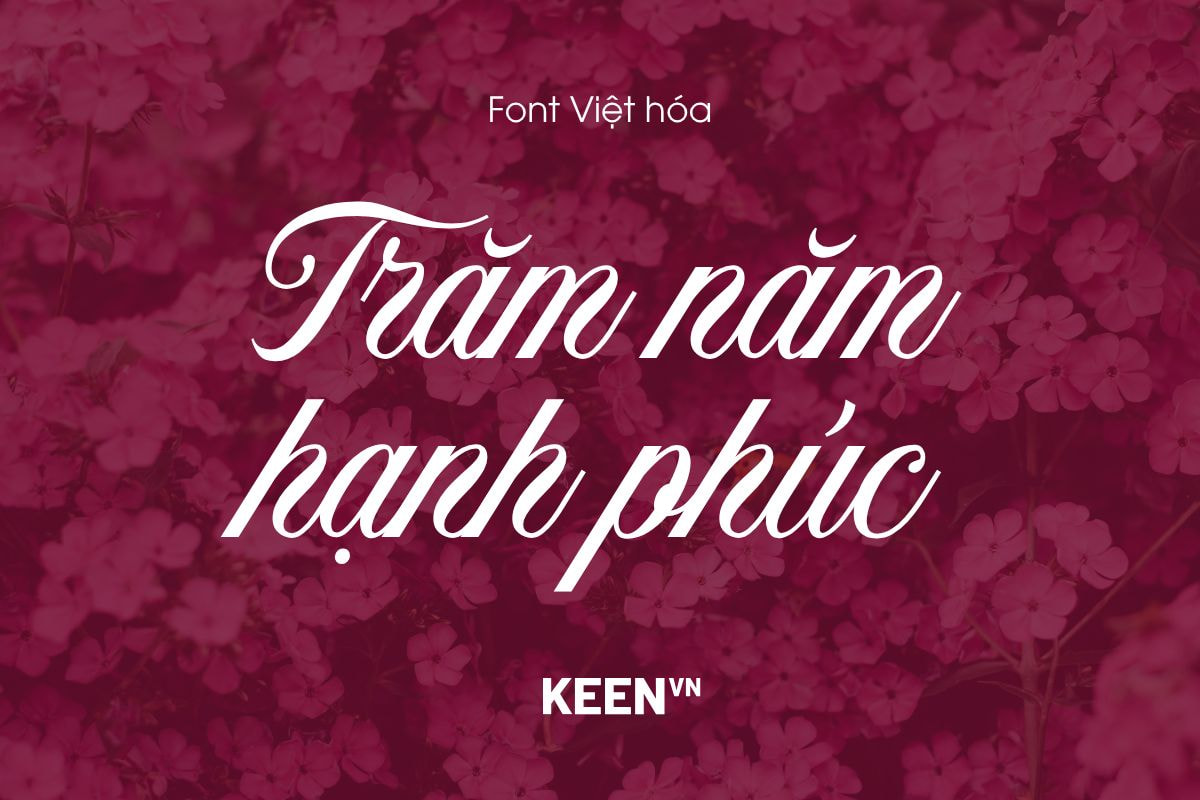
Font Việt hóa NVN Neography
- Hỗ trợ đầy đủ dấu tiếng Việt
Neography là một font script đẹp với các nét được thiết kế ấn tượng giống như chữ viết tay thật. Phông chữ này được tạo ra hoàn hảo để áp dụng cho các thiết kế khác nhau như thiệp mời, logo, tạp chí, sách, thiệp cưới và trong nhiều thiết kế khác nhau.